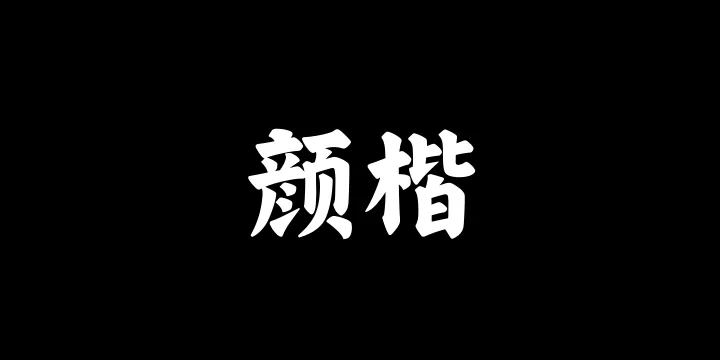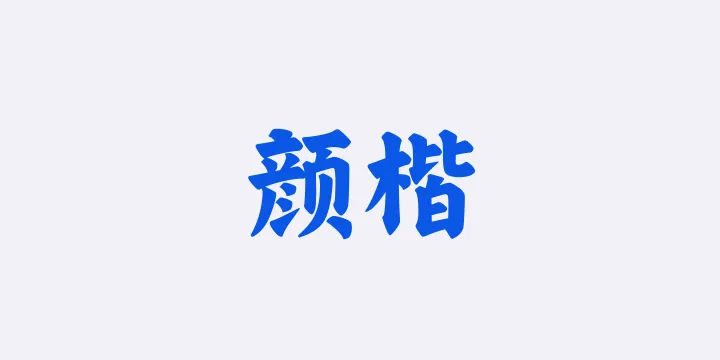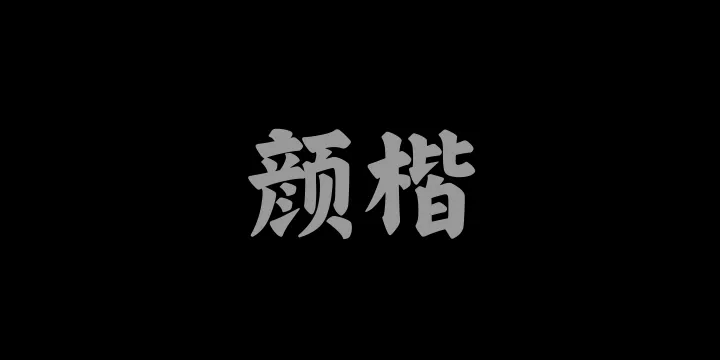
山海颜楷W By 山海字库 商用字体
字体全名: 山海颜楷W
字体简介: 山海颜楷,是一款全新的楷书字体,包含汉字9169个,符号200+个。该字体汲取中国唐代书法家颜真卿书法的颜体之特性,在汲取中创新,结合当代设计视觉环境,融入现代审美。字形方正,端庄严谨,古朴大方,起落顿笔有棱角。在饱有笔墨之意的同时,又刚柔并济。其结构方正茂密,笔画横轻竖重,笔力浑厚,挺拔开阔雄劲。三载创作,只为再现千年前大唐书法最高峰之风韵。